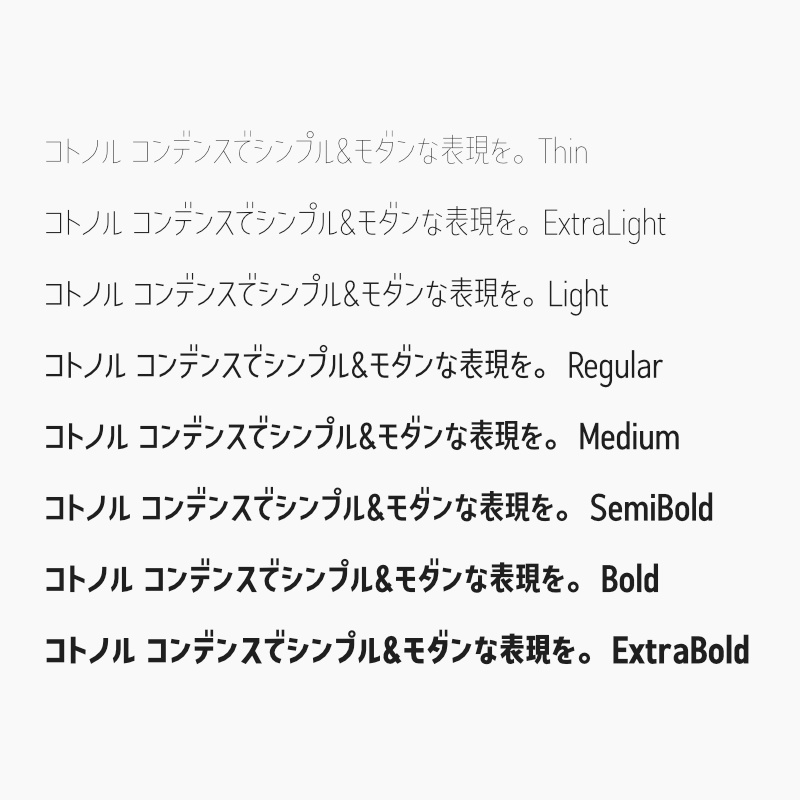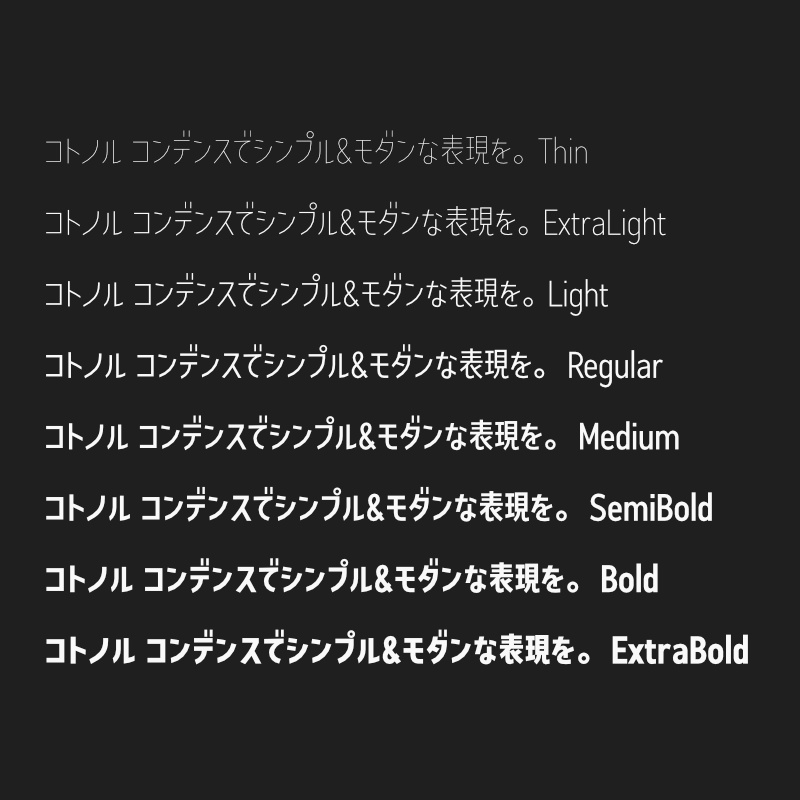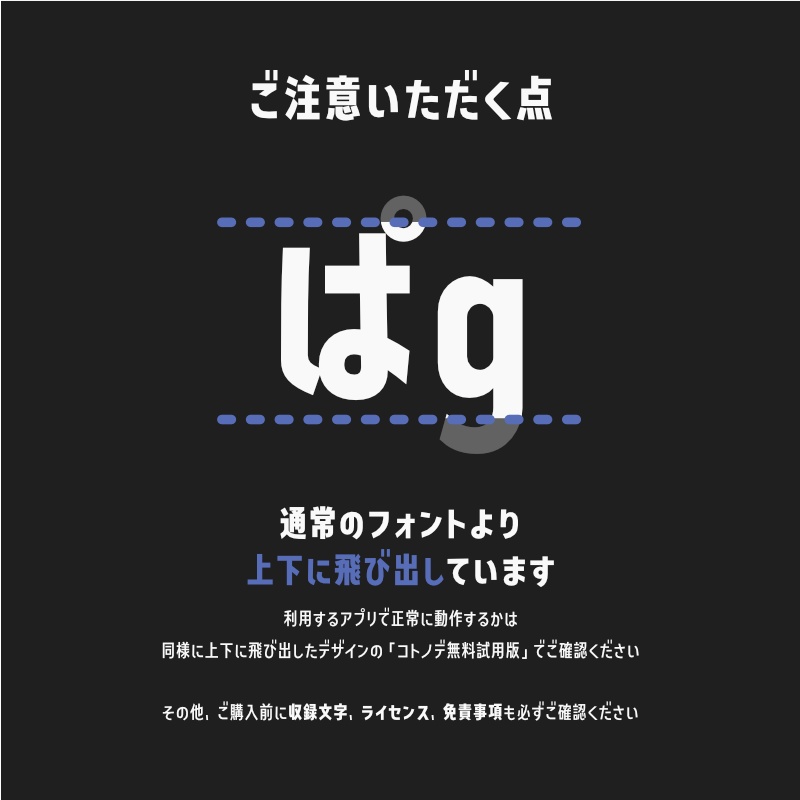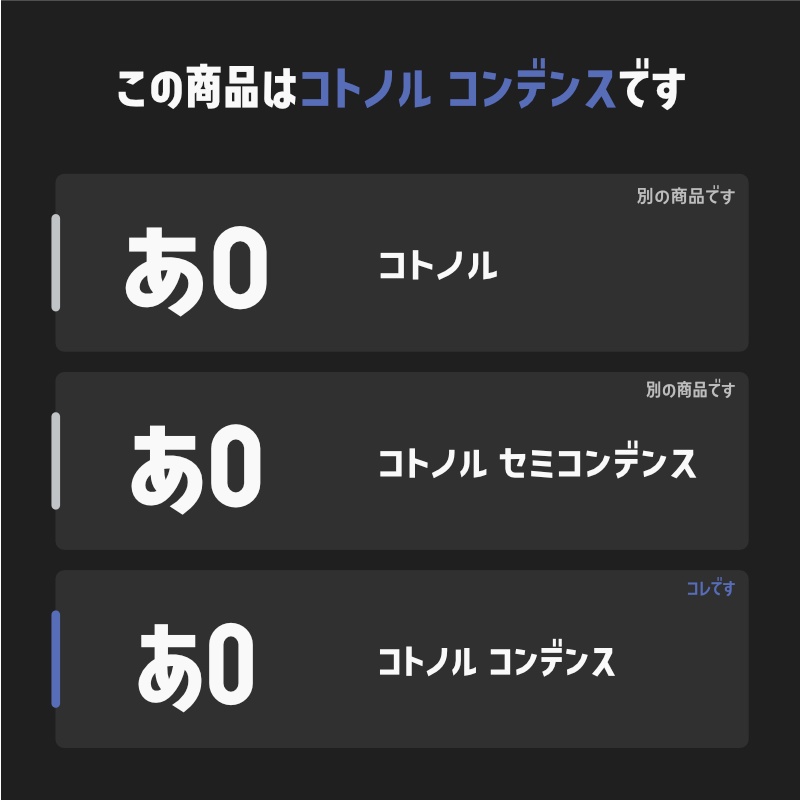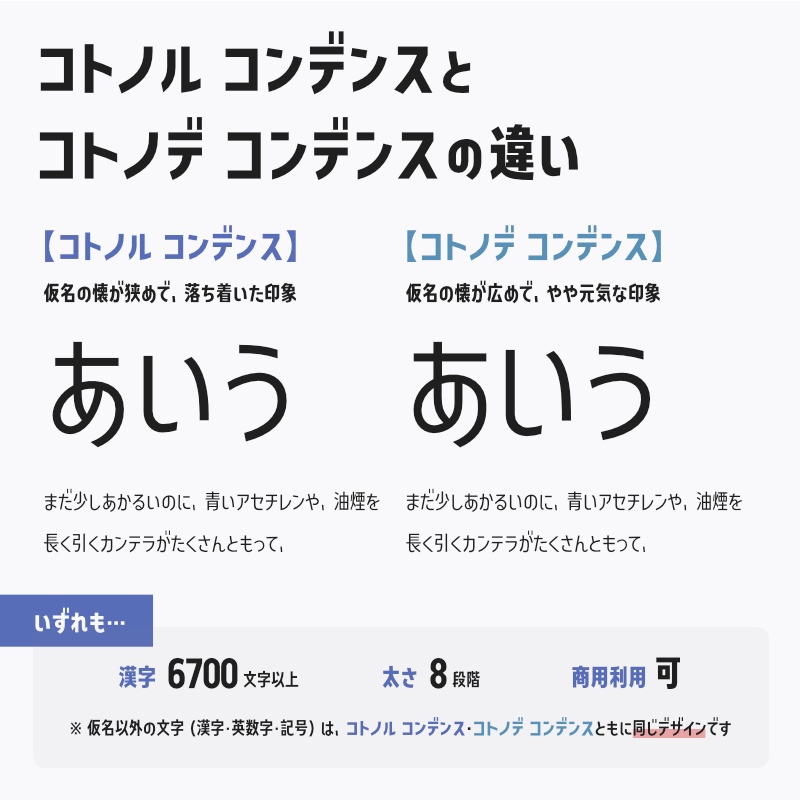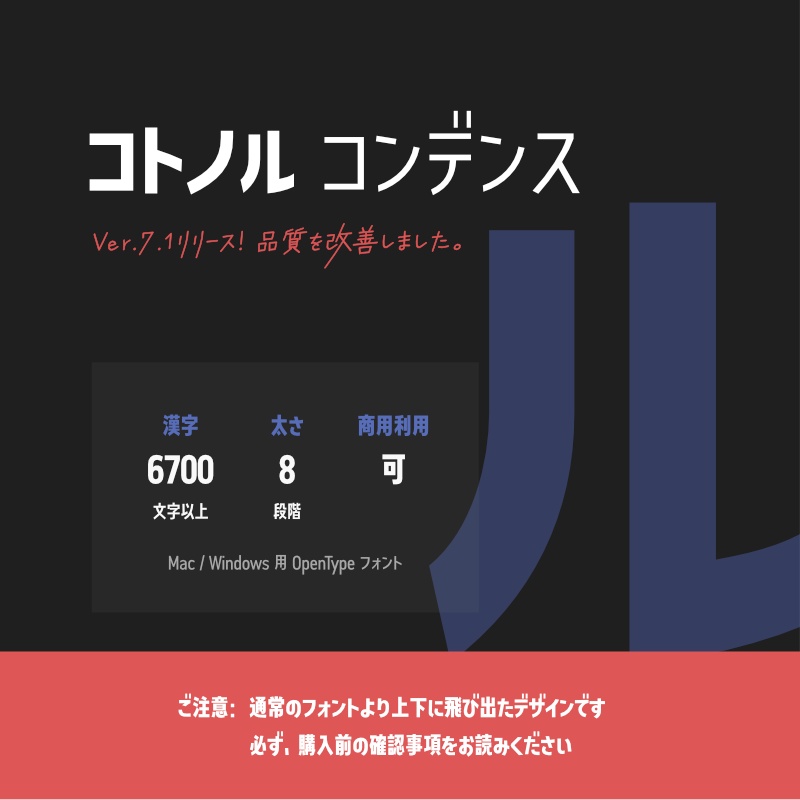
「コトノル コンデンス」フォント(漢字あり) ~縦長でかっこいいゴシック体~
・通常のフォントよりも上下にはみ出たデザインです。ご利用のアプリによっては上下が見切れることがあります。ご購入前に確認したい場合は、同様に上下にはみ出たデザインの「コトノデ無料試用版(※)」をご活用ください。 ・漢字は6,700文字以上収録しており、常用漢字・JIS第一水準漢字・JIS第二水準漢字をカバーしています。収録文字は公式の紹介ページをご確認ください。 ・公式の紹介ページの利用規約・免責事項を必ず確認してください(商用利用可・再配布禁止)。 【公式の紹介ページ】 https://kotonohaworks.com/kotonoru-condensed.html (※コトノデ無料試用版) https://dkf.booth.pm/items/2727320(無料試用版に漢字は含まれていません。)